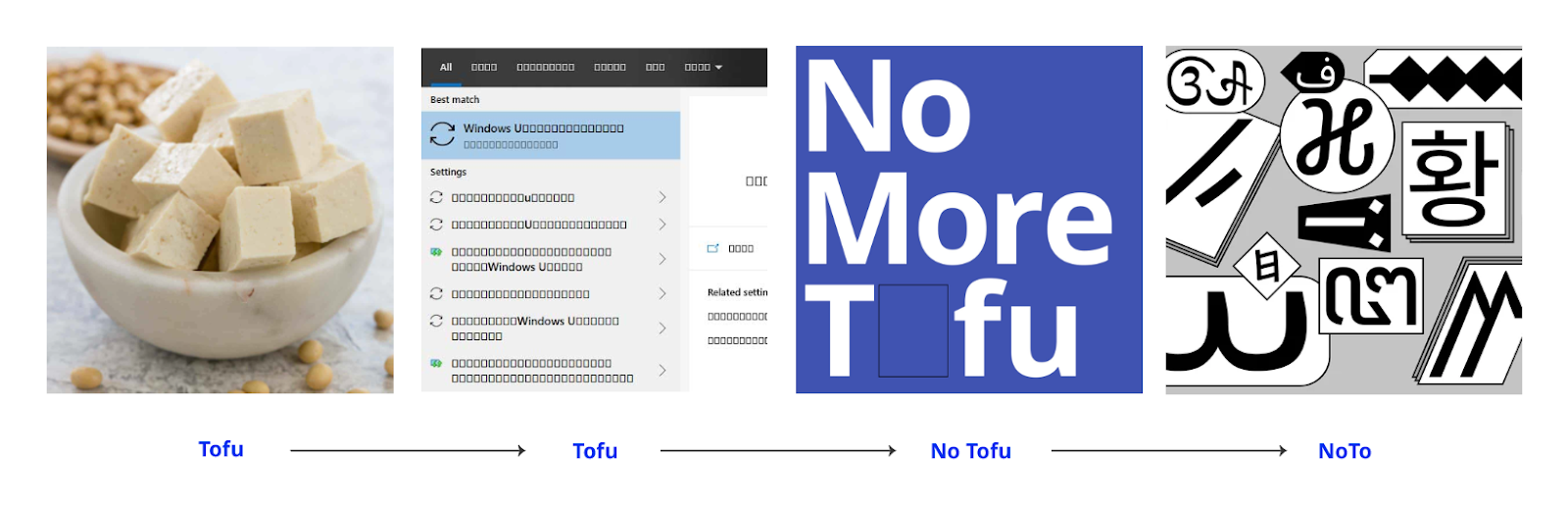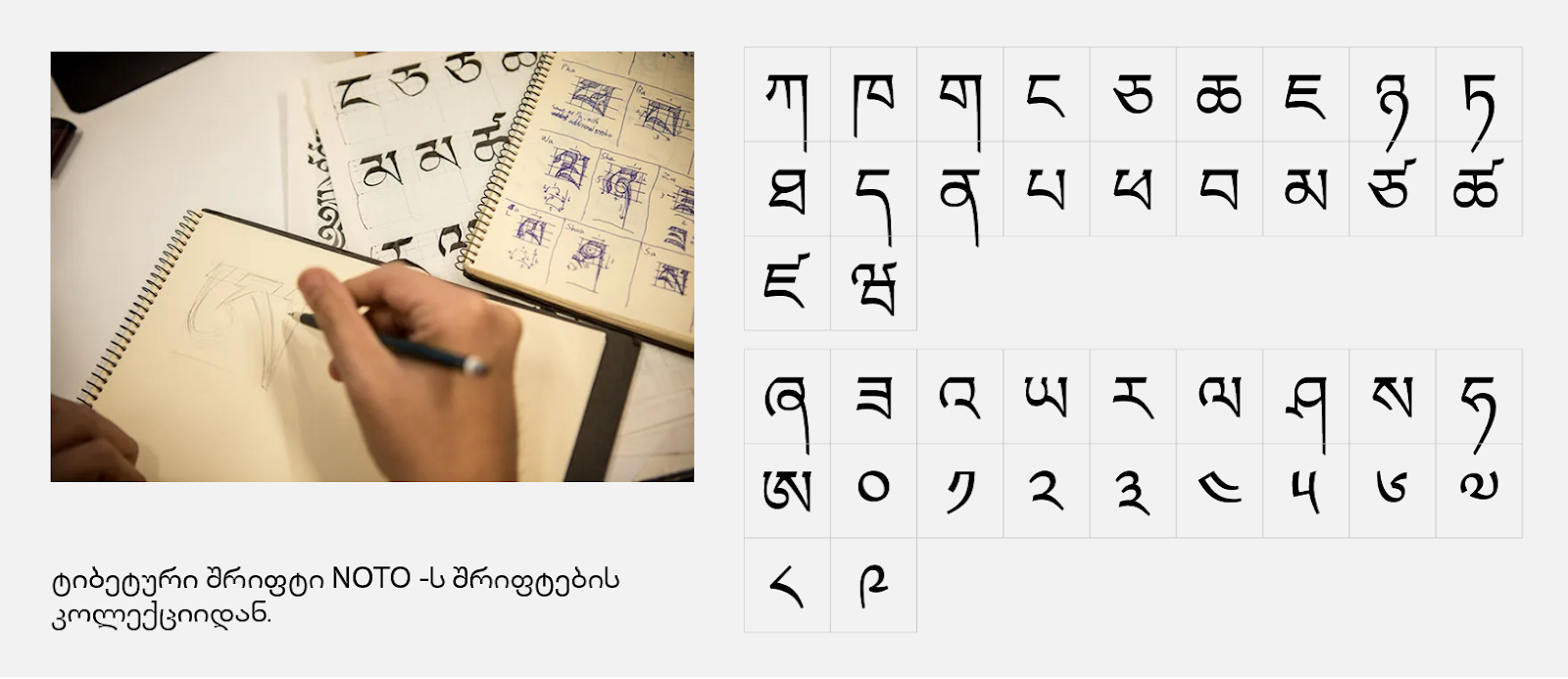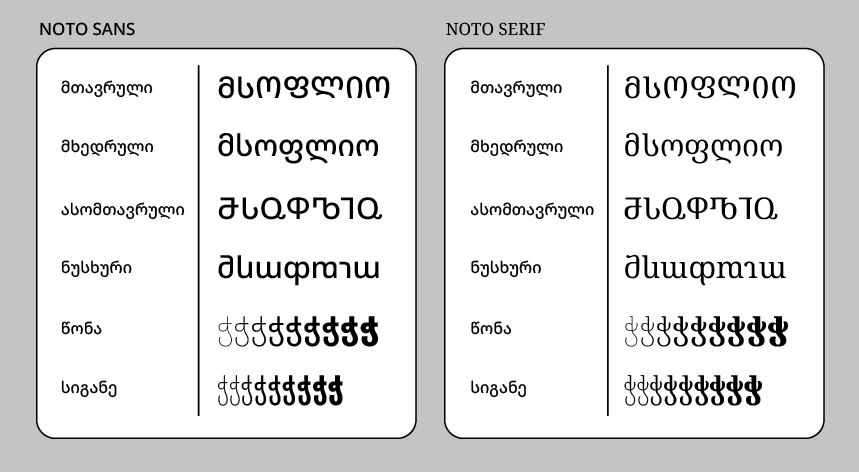
Noto არის Google-ს პროექტი, რომელიც დაიწყო 2012 წელს და დღესაც გრძელდება. პროექტის მიზანა ყველა დამწერლობისთვის მაღალი ხარისხის შრიფტის შექმნა, რომელიც აისახება Unicode სისტემაში ყველა საჭირო სიმბოლოთი და ექნება ერთმანეთთან მიმართებაში ჰარმონიული ვიზუალი.
Google-ის მიზანი იყო შეექმნა შრიფტის ვარიანტი მსოფლიოში არსებული ყველა დამწერლობისთვის. ეს შრიფტები გაერთიანდებოდა ერთ დიდ ოჯახში და ხელმისაწვდომი იქნებოდა ყველა კომპიუტერზე.
პრობლემა მდგომარეობდა იმაში, რომ ზოგიერთი შრიფტის გამოყენებისას კომპიუტერულ ტექნოლოგიებში ასოების მაგივრად იწერებოდა მართკუთხედები, რადგან დივაისებს არ ჰქონდათ ამ ენის შრიფტზე წვდომა.
მართკუთხედებს ადარებდნენ ტოფუს — აზიურ საჭმელს, რომელიც ოთხკუთხედი ფორმისაა. ანუ ყველა დამწერლობის შრიფტის შექმნით არცერთი დამწერლობის შრიფტის აკრეფისას აღარ იქნებოდა ტოფუ ასოების ადგილას No Tofu – NoTo.
ნოტოს სახელი, ასევე, ეხმიანება ლათინურ სიტყვა “noto”-ს, რაც ნიშნავს „ვწერ, აღვნიშნავ“.
Noto ოჯახი მოიცავს 100-მდე შრიფტს. ფარავს 1000-ზე მეტ ენას და 162 დამწერლობას, მათ შორის, ქართულსაც. შრიფტები კოდირებულია Unicode სტანდარტით.
შრიფტების დიზაინი Google-მა შეიმუშავა Monotype, Adobe და მსოფლიოს უამრავ წამყვან სპეციალისტთან ერთად.
UNESCO-ს მონაცემებით, მსოფლიოს დაახლოებით 6000 სალაპარაკო ენიდან 43%-ს მაინც გაქრობის საფრთხე ემუქრება. შრიფტი — ანუ სიმბოლოების ნაკრები, დღეს მთავარ როლს თამაშობს დამწერლობის შენარჩუნებაში.
იშვიათი დამწერლობის მქონე კულტურებისთვის შრიფტის არსებობა კარგი შესაძლებლობაა დამწერლობის გასაციფრულებლად და ინტერნეტ სივრცეში „შესანახად“. შრიფტის დახმარებით ენის წარმომადგენლებს შეუძლიათ გააციფრულონ წერილობითი დოკუმენტები, გამოაქვეყნონ კულტურული და რელიგიური ტექსტები ინტერნეტ სივრცეში, შექმნან დამწერლობის და ენის ციფრული სასწავლო მასალა. ეს ეხმარება ენის მატარებლებს შეინარჩუნონ თაობებს შორის კავშირი საცხოვრებელი ლოკაციების ცვლილების მიუხედავად.
Noto ოჯახი აერთიანებს უამრავი ასეთი იშვიათი დამწერლობის შრიფტს. მაგალითისთვის, ტიბეტური დამწერლობა შრიფტის სახით არ არსებობდა, ნოტოს ტიბეტური შრიფტის სახეობა შეიქმნა ტიბეტური ხელნაწერებიდან. დღეს ამ შრიფტს დღეს ყოველდღიურად ასობით ადამიანი იყენებს ტექსტურ შეტყობინებებში, ინტერნეტ სივრცეში ნავიგაციისთვის და ენის სასწავლებლად.
ნოტოს ქართულ ვარიანტზე იმუშავა აკაკი რაზმაძემ სტუდია Monotype-თან ერთად. ქართული NOTO-ს ჯგუფი შეიცავს სხვადასხვა წონის და სიგანის ქართულ ასოებს. ხელმისაწვდომია როგორც serif, ასევე sans serif სტილი.
მთლიანად მოიცავს უნიკოდის ქართულ სექციას: მხედრული, მხედრულის მთავრული, ასომთავრული და ნუსხური სიმბოლოები, ასევე - დიაკრიტიკული ნიშნები, რომლებიც გამოიყენება კომბინირებული ქართული ასოების დასაწერად (სიმბოლო + დიაკრიტიკული ნიშანი, მაგ. ა̈ ე̄ ი̈)